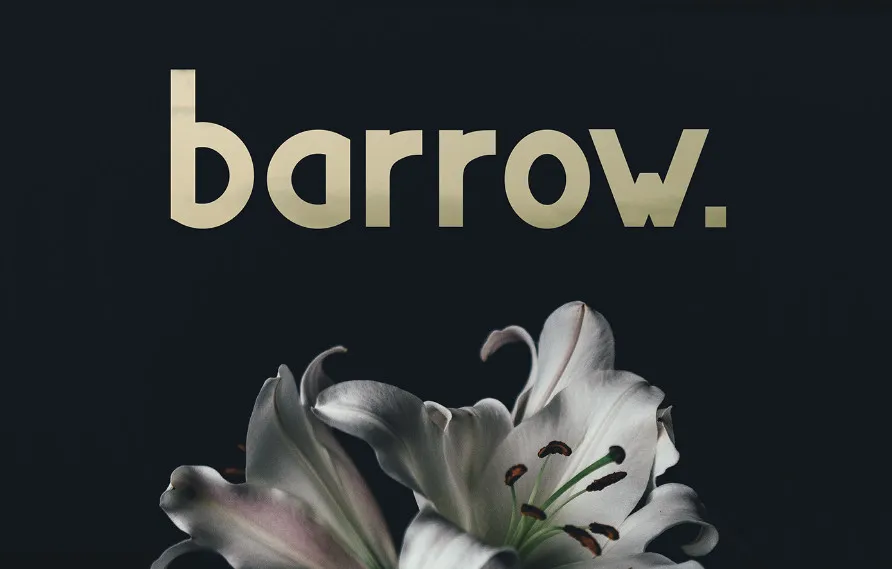
A Barrow Typeface é uma novidade na categoria das fontes sans-serif criada por Hamilton. Inspirada no elegante vintage, esta tipografia é uma fusão harmônica entre a simplicidade e a minimalismo. Desenvolvida pelo designer Szonja Balint, a Barrow oferece três pesos diferentes para uso variado: leve para um estilo moderno e fino, e bold para quando quer dar um toque mais suave à tipografia. Com letras maiúsculas e minúsculas completas, números e caracteres especiais incluídos, esta fonte é perfeita tanto para projetos profissionais quanto para trabalhos pessoais que valorizam a simplicidade. Aproveite esses diferentes pesos para criar um visual único e elegante em seu design.